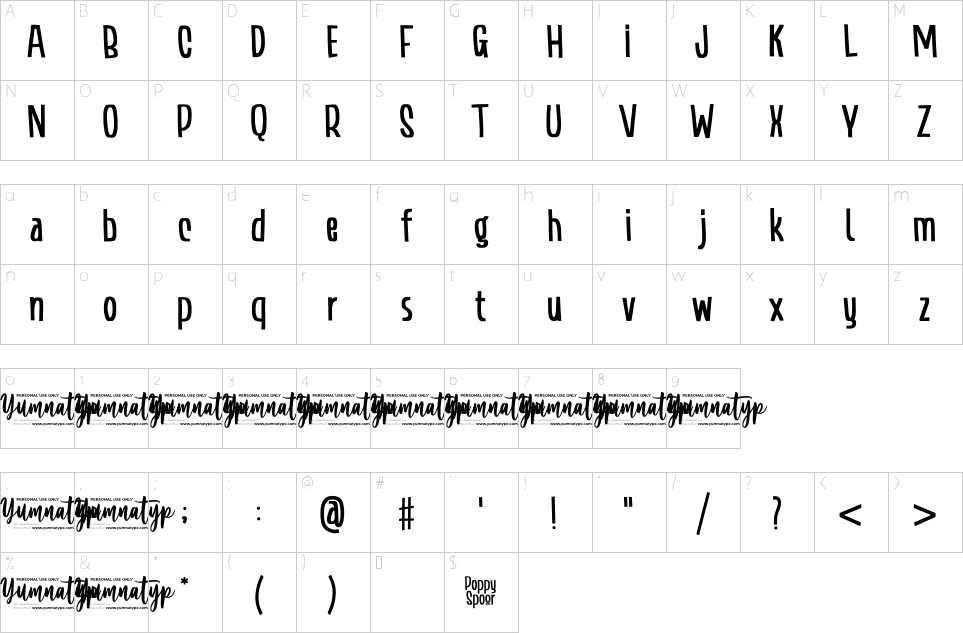
Descubra a fonte Poppy Spoor, uma delícia para designers e amantes da tipografia. Desenhada pela Yumna Type, esta fonte foi especialmente concebida para oferecer uma escrita alegre e agradável aos projetos digitais e impressos. Com seu estilo suave e personalizado, Poppy Spoor é perfeito para criar designs que transmitem alegria e entusiasmo. Esta fonte está disponível gratuitamente para download tanto para Windows quanto para Mac, permitindo que você a personalize para seus projetos mais criativos. Mais de 845 pessoas já experimentaram o prazer de usar Poppy Spoor, e agora é sua vez de experimentar e descobrir por si mesmo. Se você está buscando uma fonte que traga um toque especial às suas criações, Poppy Spoor é uma opção incrível para considerar. Descubra a sua versão e adicione alegria ao seu trabalho.